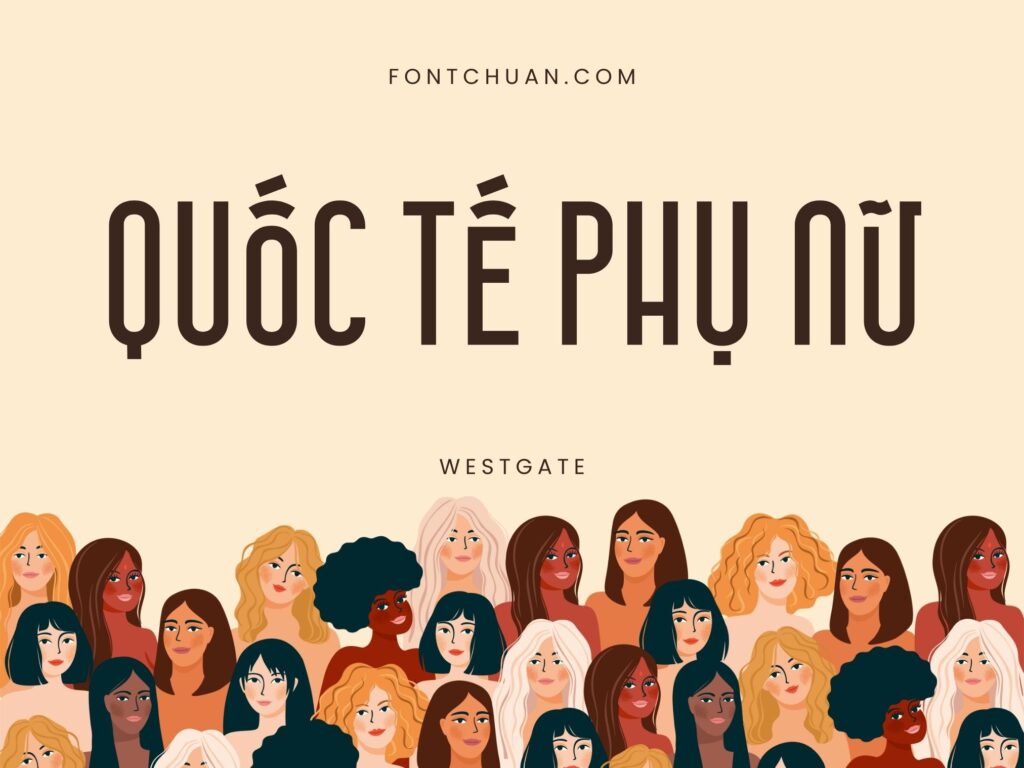
Font Westgate Trọn Bộ Font Tiếng Việt
Westgate là một Font chữ bất động sản thuộc nhóm sans-serif, được thiết kế bởi Behalf Studio, lấy cảm hứng từ kiểu chữ bê tông trên các cổng Bắc, Đông và Tây của chợ Bến Thành, Sài Gòn. Font mang phong cách Art Deco với các nét chữ cao, mảnh và hình học, tạo nên sự thanh lịch, hiện đại và mang đậm dấu ấn kiến trúc đô thị – yếu tố thường thấy trong các thiết kế nhận diện thương hiệu bất động sản cao cấp. Westgate hỗ trợ đầy đủ tiếng Việt cùng nhiều ngôn ngữ khác, được sưu tầm và đăng bởi thành viên của Font Chuẩn.
Font có thiết kế chữ đậm, các đường nét góc cạnh và hình học rõ ràng, tạo nên sự nổi bật và dễ đọc. Westgate phù hợp cho các thiết kế liên quan đến thương hiệu, tiêu đề, poster và các ấn phẩm truyền thông cần sự mạnh mẽ và hoài cổ. Các ngành nghề như quảng cáo, bất động sản, giáo dục và công nghệ có thể tận dụng hiệu quả font này. Ngoài ra, Westgate cũng thích hợp cho các sự kiện như lễ hội, sinh nhật, ngày Nhà giáo và Valentine.